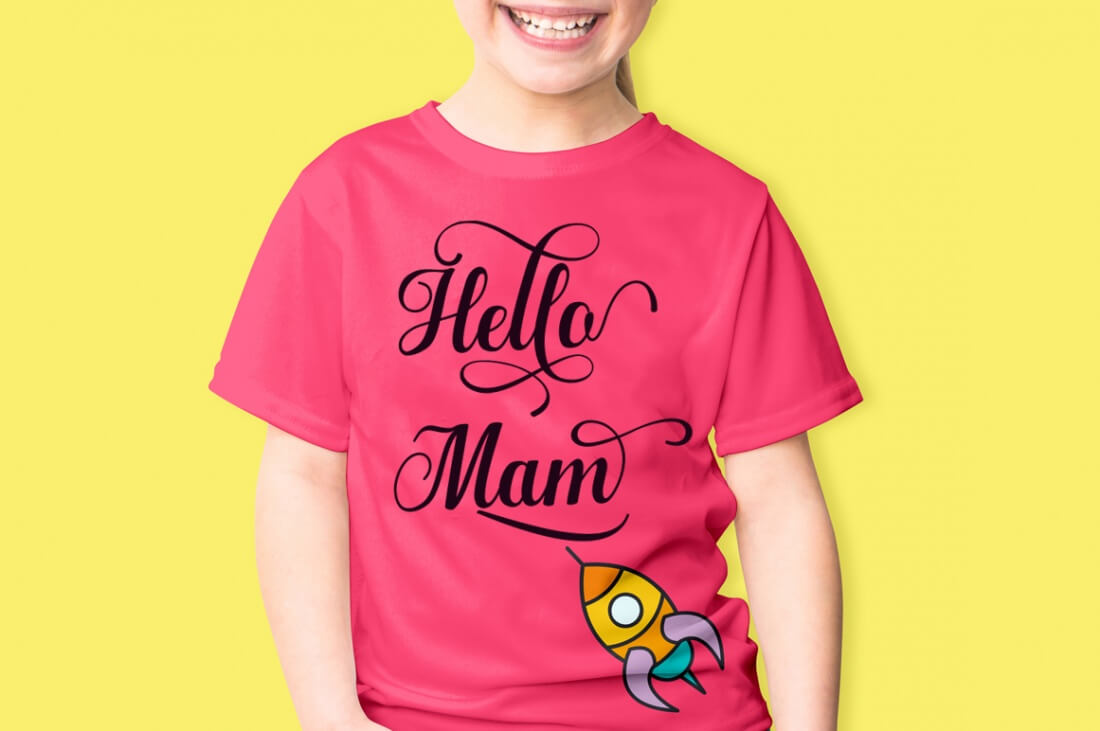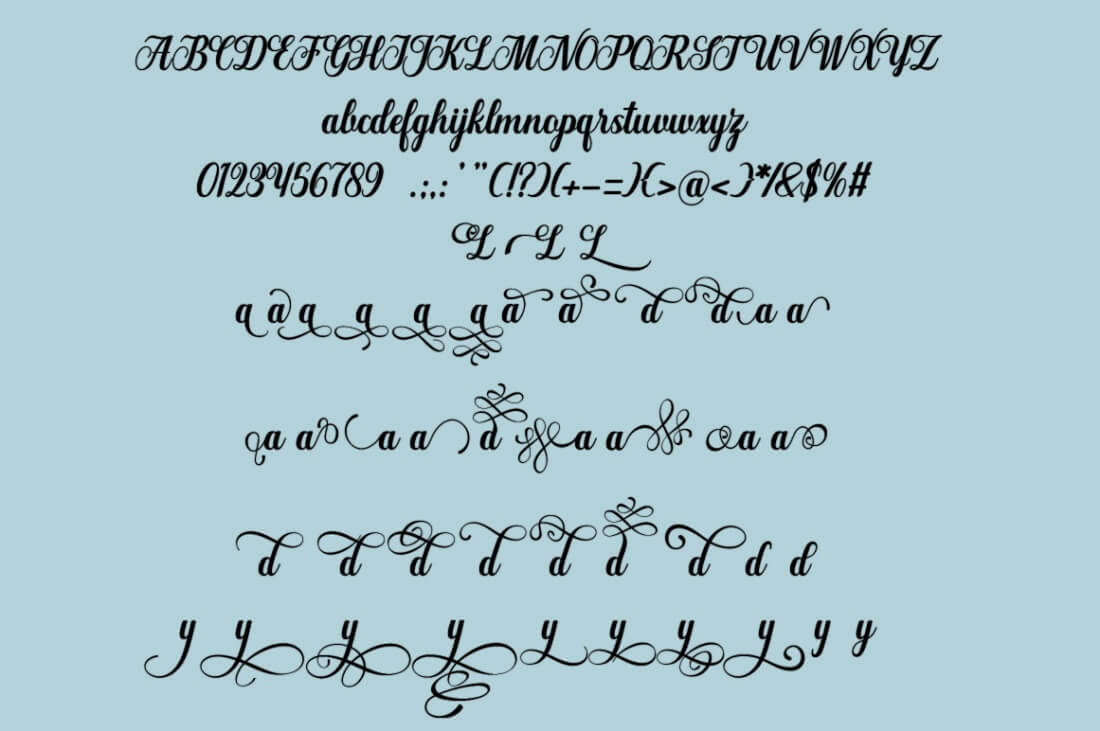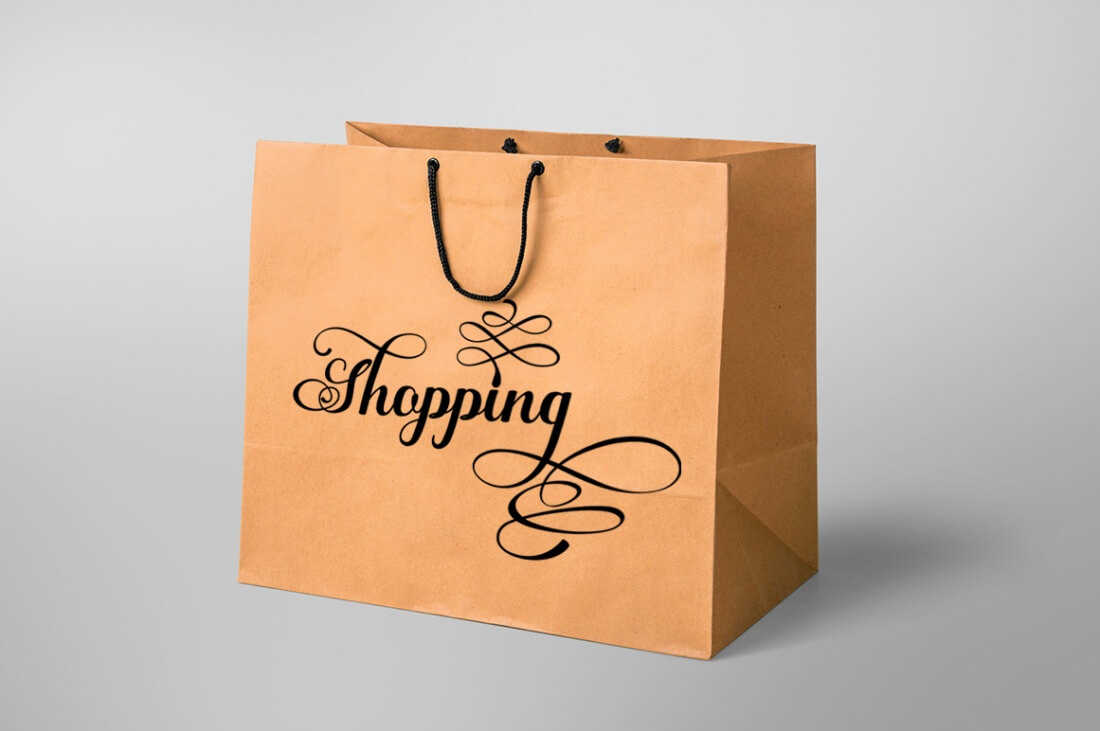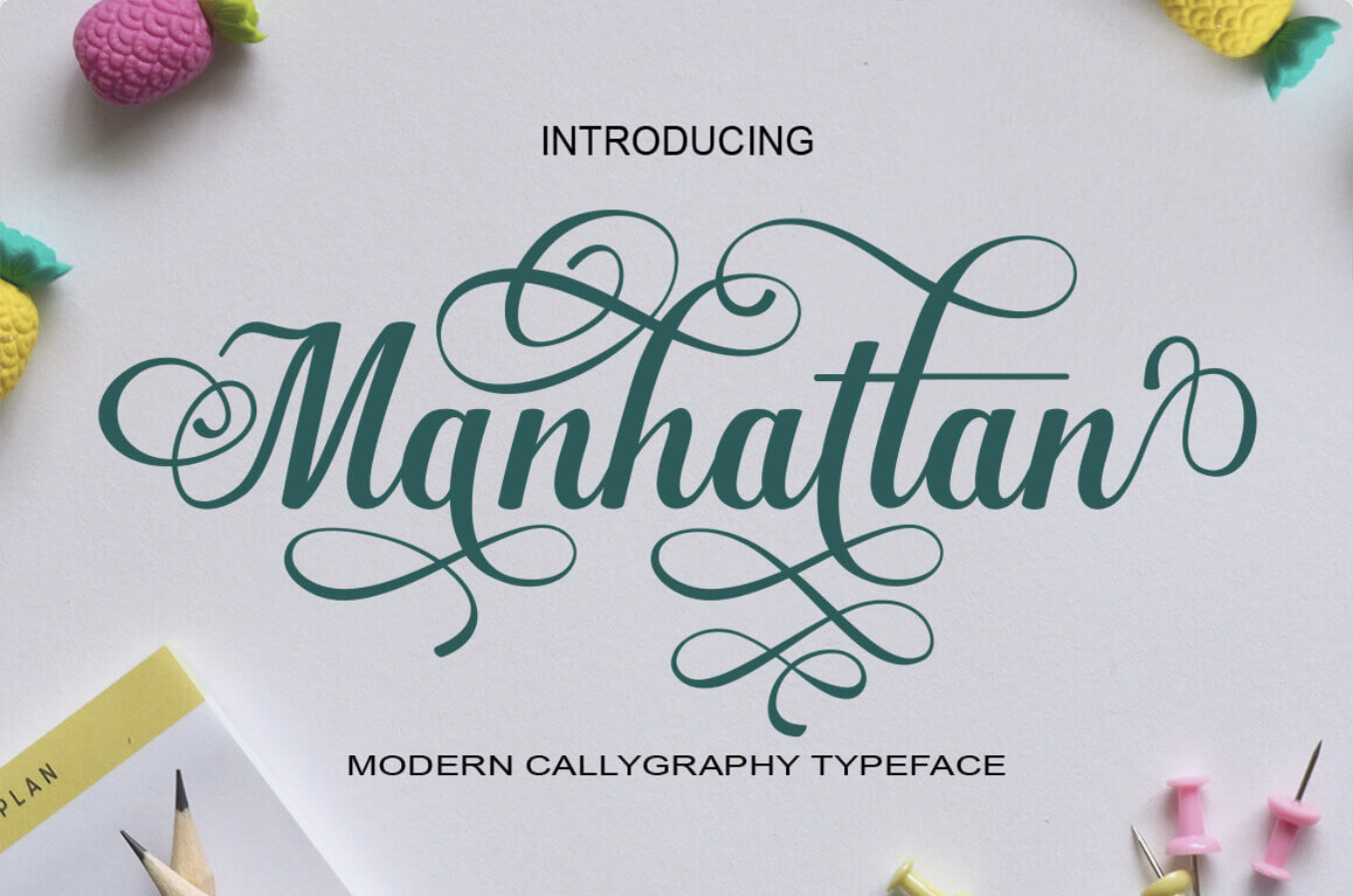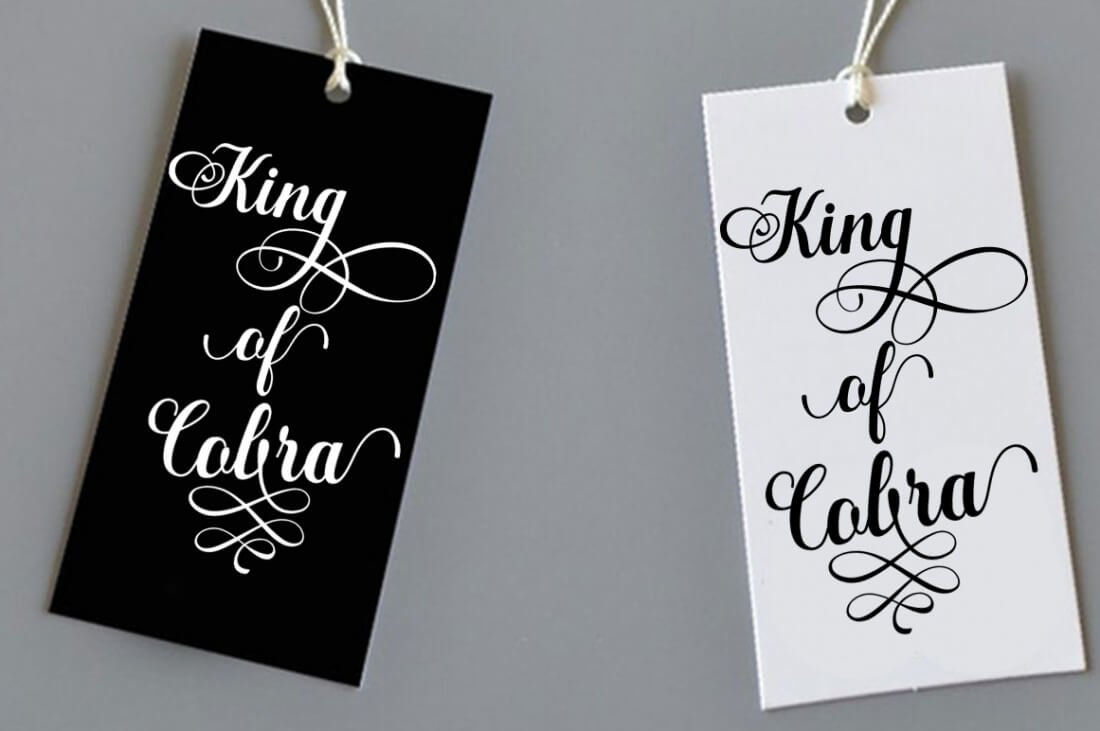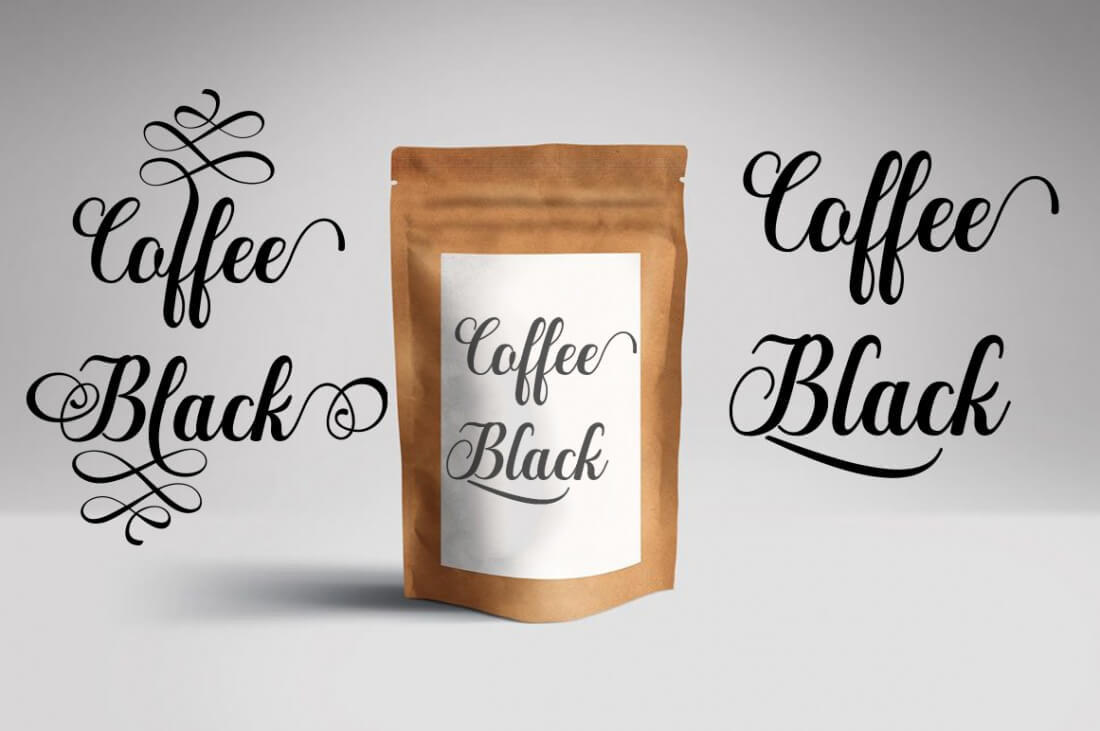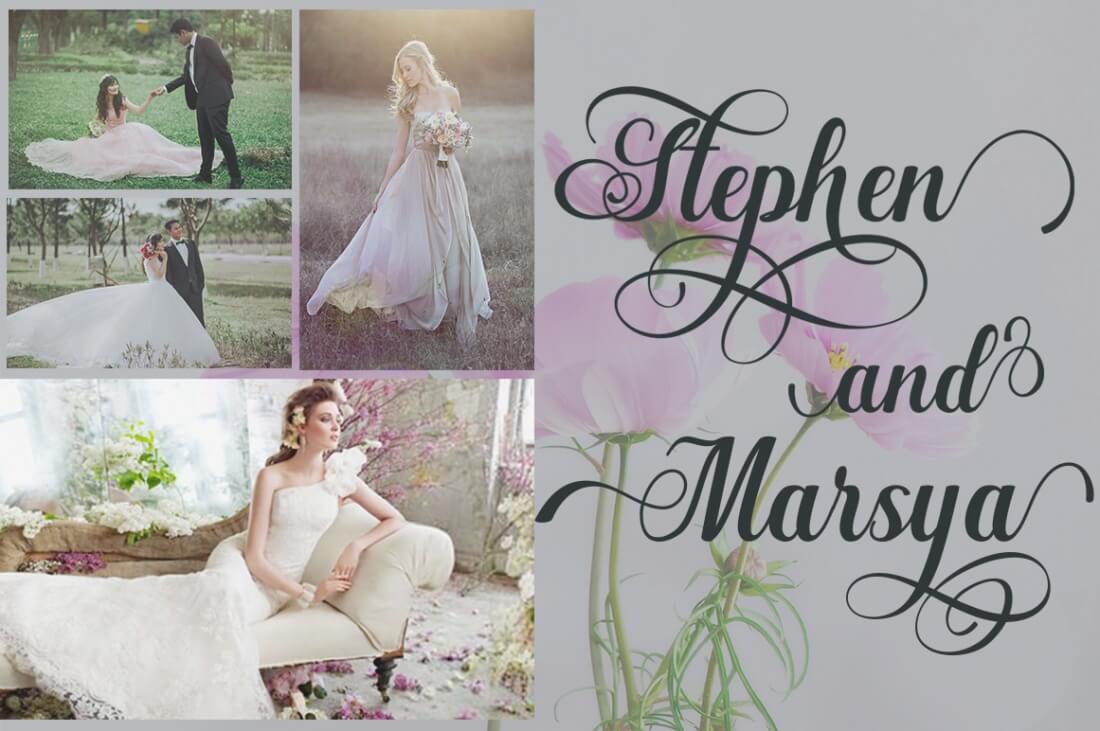
Элегантный, Современный Каллиграфический Шрифт с 833 Глифами
Elegant, Modern Calligraphy Font Manhattan
Основные моменты:
Красивый и элегантный современный шрифт каллиграфии.
Нагрузки функций OpenType, включая перекосы, лигатуры, альтернативные стили, числители, надстрочные, подстрочные и многое другое.
883 уникальных глифа.
Отличный выбор для множества печатных проектов - водяные знаки, свадебные приглашения, логотипы, визитные карточки, теги, футболки и т. Д.
Набор включает в себя прописную и строчную международную подпись, знак пунктуации поддержки.
• Beautiful and elegant modern calligraphy typeface.
• Loads of OpenType features including swashes, ligatures, alternative styles, numerators, Superscripts, Subscripts and more.
• 883 unique glyphs.
• Excellent choice for a variety of printed projects - watermarks, wedding invitations, logos, business cards, tags, T-shirts, etc.
• Set includes uppercase and lowercase international signature, symbol punctuation support.